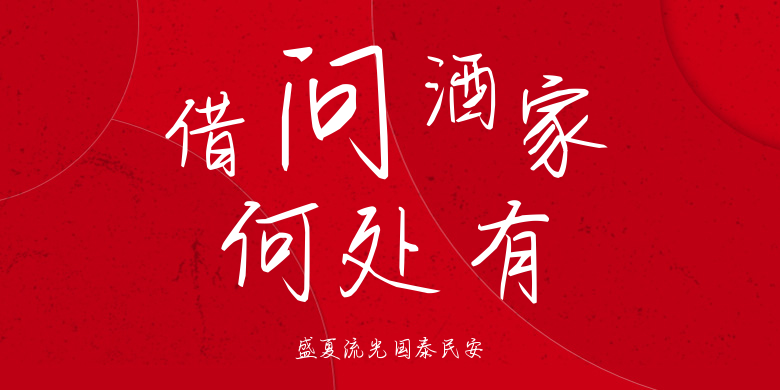
盛夏流光国泰民安
盛夏流光国泰民安,这款字体结构工整、笔画清晰,兼顾美观与易读性,适用于标题、正文、海报、包装、LOGO 等多种场景。字形优雅稳定,风格百搭耐看,适配日常排版与创意设计,让文字呈现更舒适、更具质感。盛夏流光国泰民安一笔一画,皆是细节,以均衡的比例、流畅的线条打造舒适视觉体验,字形端正大气,风格简约现代。无论是商业设计、品牌宣传还是日常排版,都能轻松驾驭,让文字更有格调与力量。盛夏流光国泰民安字体下载。